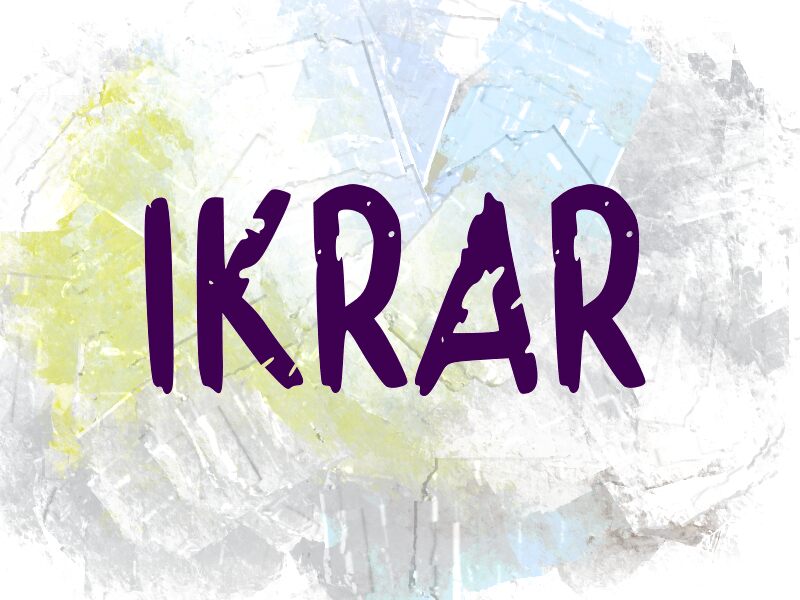
IKRAR
Ikrar, conçue par Wep, est une police pinceau gratuite aux traits irréguliers et aux bords effilochés qui confèrent à chaque caractère un rythme artisanal, presque brut. Ses formes sont acérées et asymétriques, avec des angles saillants et une texture usée qui empêchent le lettrage de paraître trop lisse ou trop fini.
Ikrar est idéale pour des titres d'affiches, des visuels musicaux, du graphisme streetwear, des flyers d'événements et des accents de logos percutants où la texture brossée fait toute la différence. Cette police gratuite est également parfaite pour des citations courtes, des en-têtes de réseaux sociaux et des étiquettes de packaging lorsque vous recherchez un rendu manuscrit brut tout en conservant une structure claire et lisible.